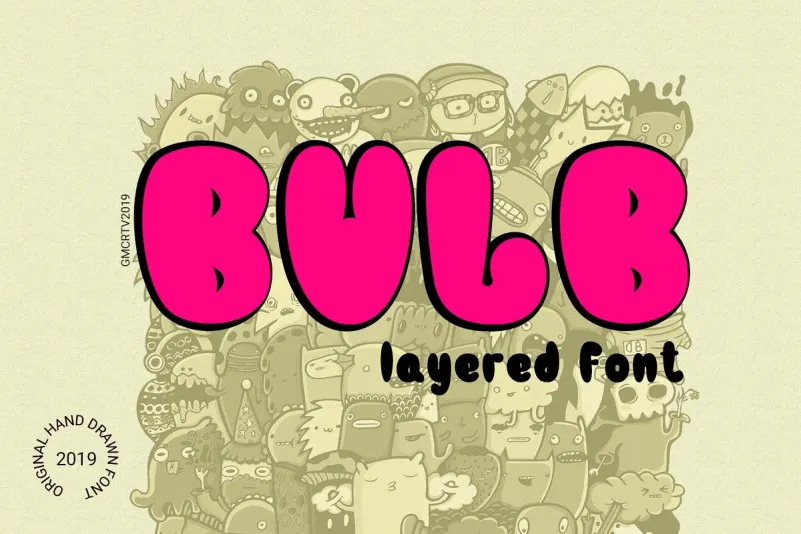
Introduzimos a Bulb Typeface. Esta é uma fonte sem serif criada pelo Designer 178-MC que faz parte do gênero Playful Fonts. Inspirada na design de capas de livros antigas, esta fonte sans-serif foi projetada para se tornar mais decorativa e flexível em diversas aplicações. Perfeita tanto para exibir seus designs como produtos profissionalmente, a Bulb Typeface também é ideal para uso em logotipos, revistas, filmes, cartazes, flyers, placas de sinalização, entre outros. Essa fonte semelhante ao papel de camadas tem um design versátil que vai além da estética e se encaixa em uma variedade de contextos. Agora é o momento ideal para você adquirir a Bulb Typeface gratuitamente, ampliando suas possibilidades criativas. É fácil de usar e fica perfeitamente integrada em qualquer projeto visual, tornando-a um recurso inestimável tanto para iniciantes quanto para profissionais. Experimente incorporar uma pitadinha de charme ao seu design com a Bulb Typeface – ela é o toque final que você está procurando.